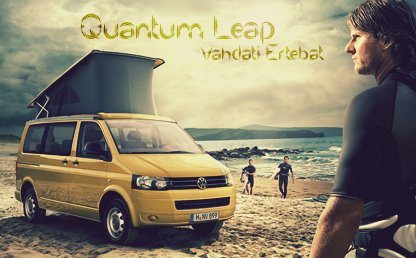
فونت زیبای Quantum Leap
Quantum Leap By Weknow
فونت Quantum Leap یکی از فونت‌های زیبا و فانتزی انگلیسی بوده که توسط Wino Sutarmin Kadir طراحی شده است . شما می‌توانید در طرح‌های خود از این فونت زیبا استفاده نمایید . امیدوارم این فونت مورد پسند شما قرار بگیرد .